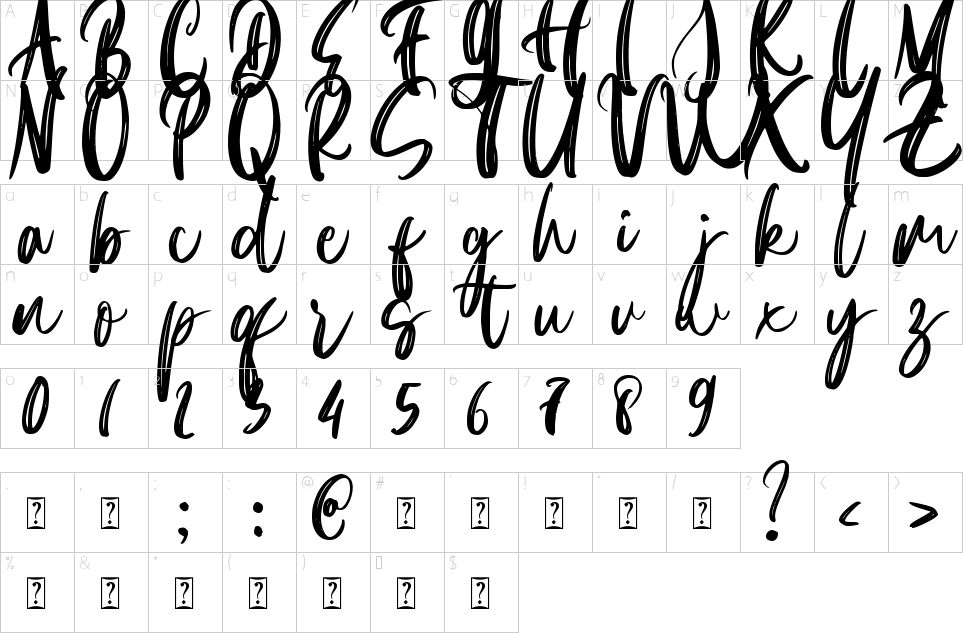
Descubra a elegância e a simplicidade da fonte Moon Stars. Esta fonte foi criada pelo designer desconhecido da Nox Studio, e você pode adquiri-la gratuitamente tanto no Windows quanto no Mac. Atraente e versátil, Moon Stars é perfeita para adicionar um toque de brilho a qualquer projeto gráfico. Com seu design arredondado e elegante, Moon Stars traz uma sensação de tranquilidade e serenidade, inspirada no luar e estrelas. Esta fonte já foi baixada 838 vezes, evidenciando seu valor e popularidade entre designers e criadores de conteúdo. Seja você um estudante de design ou um profissional, Moon Stars é a fonte perfeita para aqueles que valorizam a beleza simples e o design minimalista. Experimente hoje e faça sua própria impressão com a Moon Stars Font.